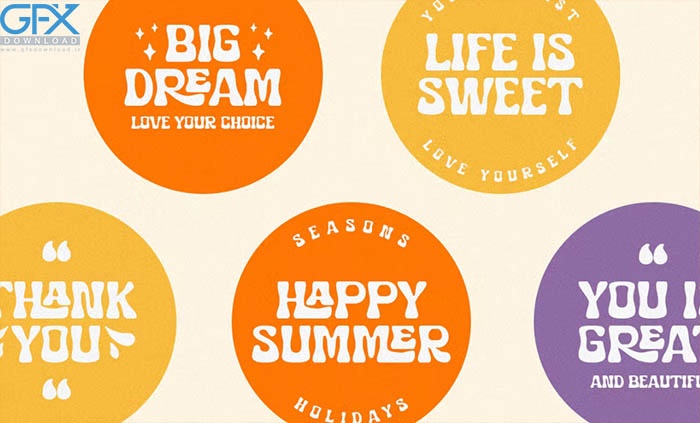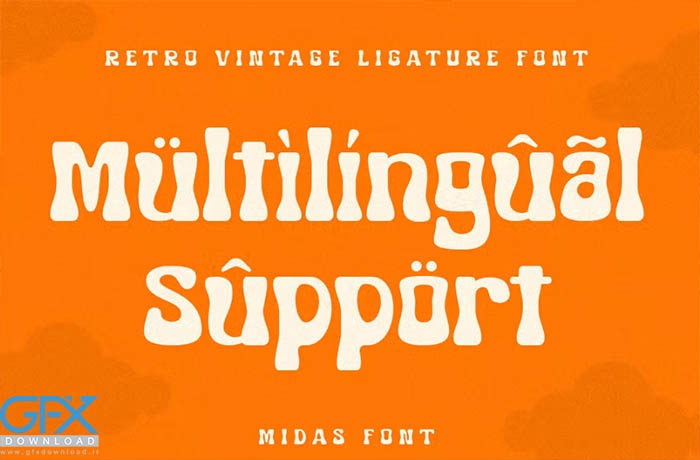
دانلود فونت به سبک وینتیج Midas این فونت با نام Midas Vintage Retro Ligature Font یک فونت معاصر با فونت فانتزی، منحصربه‌فرد و همه‌کاره است، فونت‌هایی که می‌توانید با ترکیب آن‌ها هر گونه تنوع و اشکال منحصربه‌فرد را به راحتی تنها در چند ثانیه و با انتخاب گزینه‌های جایگزین از آن‌ها به دست آورید.
این یک فونت انگلیسی نمایشگر با کنتراست متوسط است که برای پروژه های برندسازی، لوگو، طرح های عروسی، پست های رسانه های اجتماعی، تبلیغات، بسته بندی محصولات، طرح های محصول، برچسب، عکاسی، واترمارک، دعوت نامه، لوازم التحریر و هر پروژه ای عالی است.
• مجموعه کاراکتر A-Z
• حروف بزرگ و کوچک
• اعداد و علائم نگارشی
• شخصیت‌های برجسته (اروپا غربی)
• جایگزین های سبکی